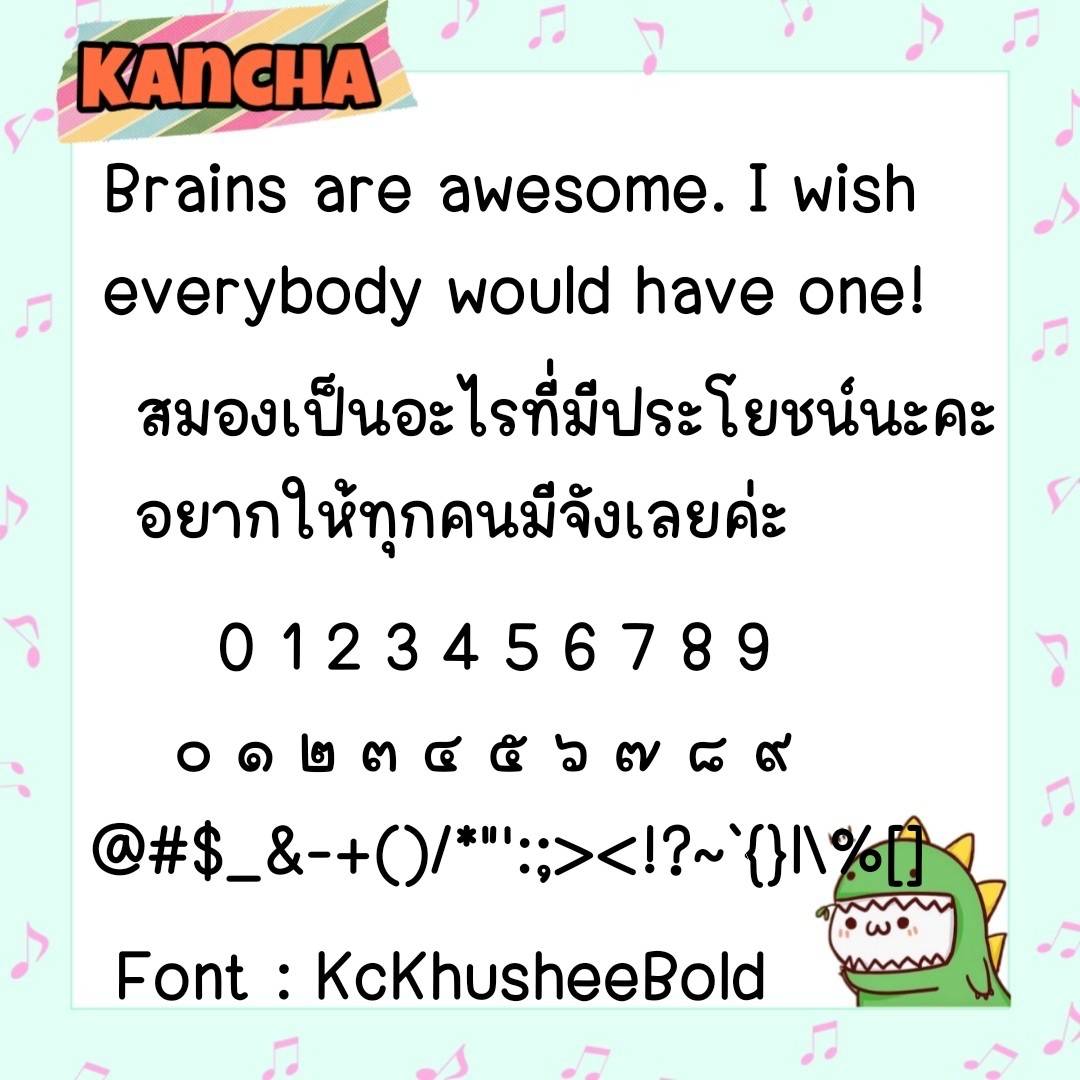
Font KcKhushee
🔸ฟอนต์แนวอ่านง่าย สบายตา ขนาดพอดี ดูเป็นระเบียบค่ะ 🥰💙
🔹 The font is easy to read, comfortable on the eyes, the right size, looks organized.🥰💙